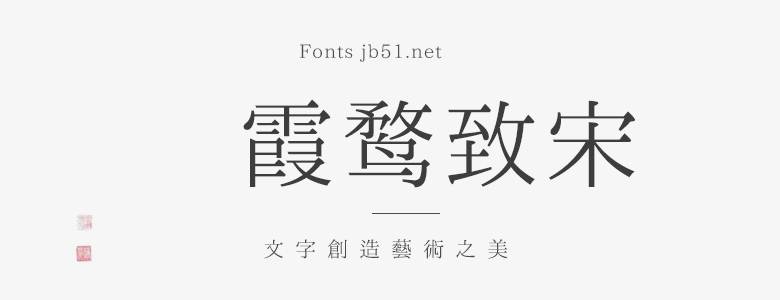
霞鶩致宋字體為IPAex 明朝字體的衍生字型項(xiàng)目,在原始字型的基礎(chǔ)上,利用原有的部件和筆形,增補(bǔ)原始字型未包含的字,并對(duì)原有的部分漢字按照舊式印刷常見(jiàn)字形進(jìn)行調(diào)整,字體文件格式為TTF,同時(shí)提供免費(fèi)在線預(yù)覽,免費(fèi)在線轉(zhuǎn)換以及免費(fèi)下載。